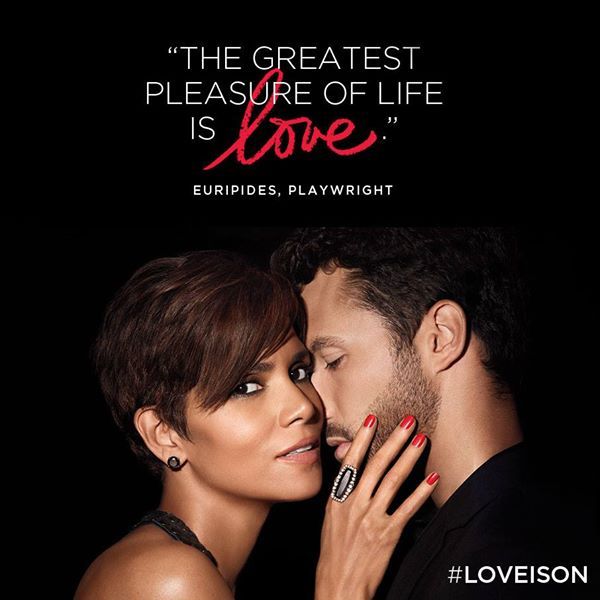
Foro de Tipografía ¿Qué tipografía es? el 24.08.2015 a las 16:18 por hola_txell · 3 comentarios Seguir este tema Dejar de seguir este tema 2 seguidores Hola! Me gustaría saber qué tipografía es la palabra "Love", o algunas tipografías parecidas. ¡Gracias! Comentar Me gusta
¡Eso pensaba yo! Pero en la misma campaña utilizan otros textos con la misma tipo... Estoy a la espera de que me pasen originales. Gracias igualmente :)
@txellgf no es ninguna tipografía: es lettering, es decir, un dibujo. Lo más cerca que tendrás como tipografía son las handwritten.